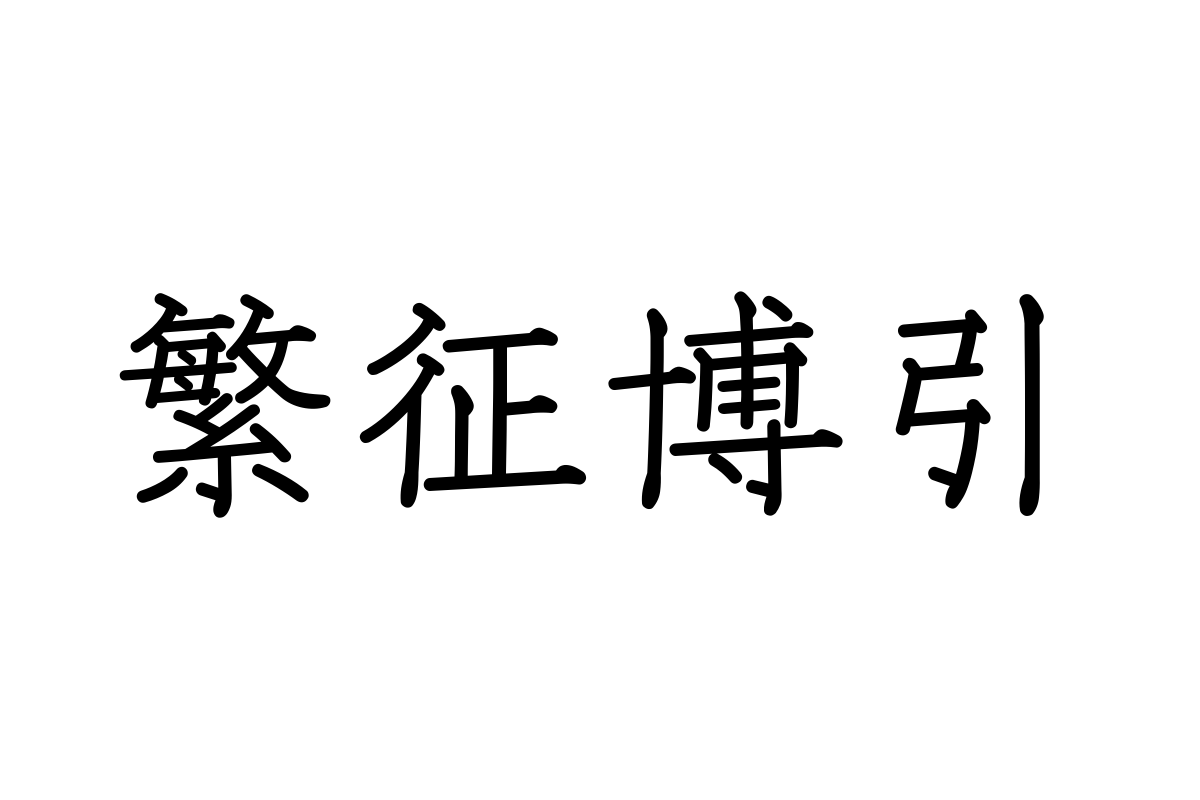
汉仪花冠-55是一款由汉仪公司设计的字体,主要用于中文排版。这款字体的特点是字形圆润饱满,线条流畅自然,给人一种优雅、大方的感觉。它的笔画粗细适中,既有力度又有弹性,既适合用于标题,也适合用于正文。此外,这款字体还具有很好的可读性,无论是在印刷还是电子屏幕上都能保持良好的视觉效果。总的来说,汉仪花冠-55是一款非常实用且美观的字体,适用于各种需要中文排版的场景。